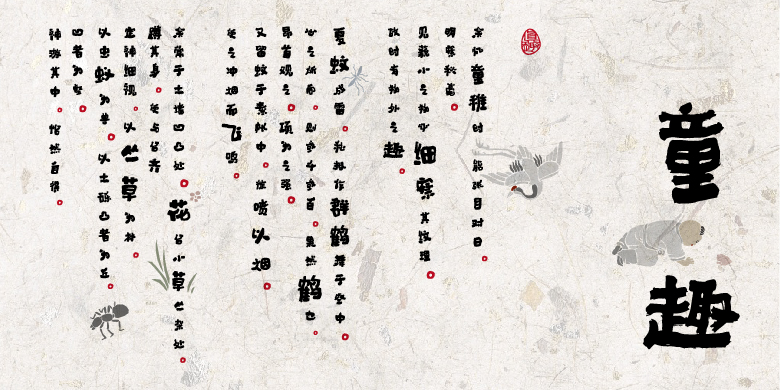
方正字迹-刘鑫标幼体
字体品牌: 方正字迹 设计师:刘鑫 字体分类:创意书写 字体属性:精品字 字符集:大陆简体(GB2312-80)、简繁扩展(GBK) 发布时间: 2019
方正字迹-刘鑫标幼体作者为书法字体设计师刘鑫,他是山东工艺美术学院专业导师,也是中国设计师沙龙CDS会员。这是一款手写书法字体,使字体字形在保证可读性的同时,对其进行了极富个性的创造,将其笔画结构进行圆润化,同时又带有书法字体固有的笔触感和机理感。故而字体风格童趣中带有一份古拙,稚气中带有一种张力,可爱顽皮又不失朴拙浑厚。极度的夸张和修饰,使字体设计感极强,不拘一格,在商业应用中实用性强。